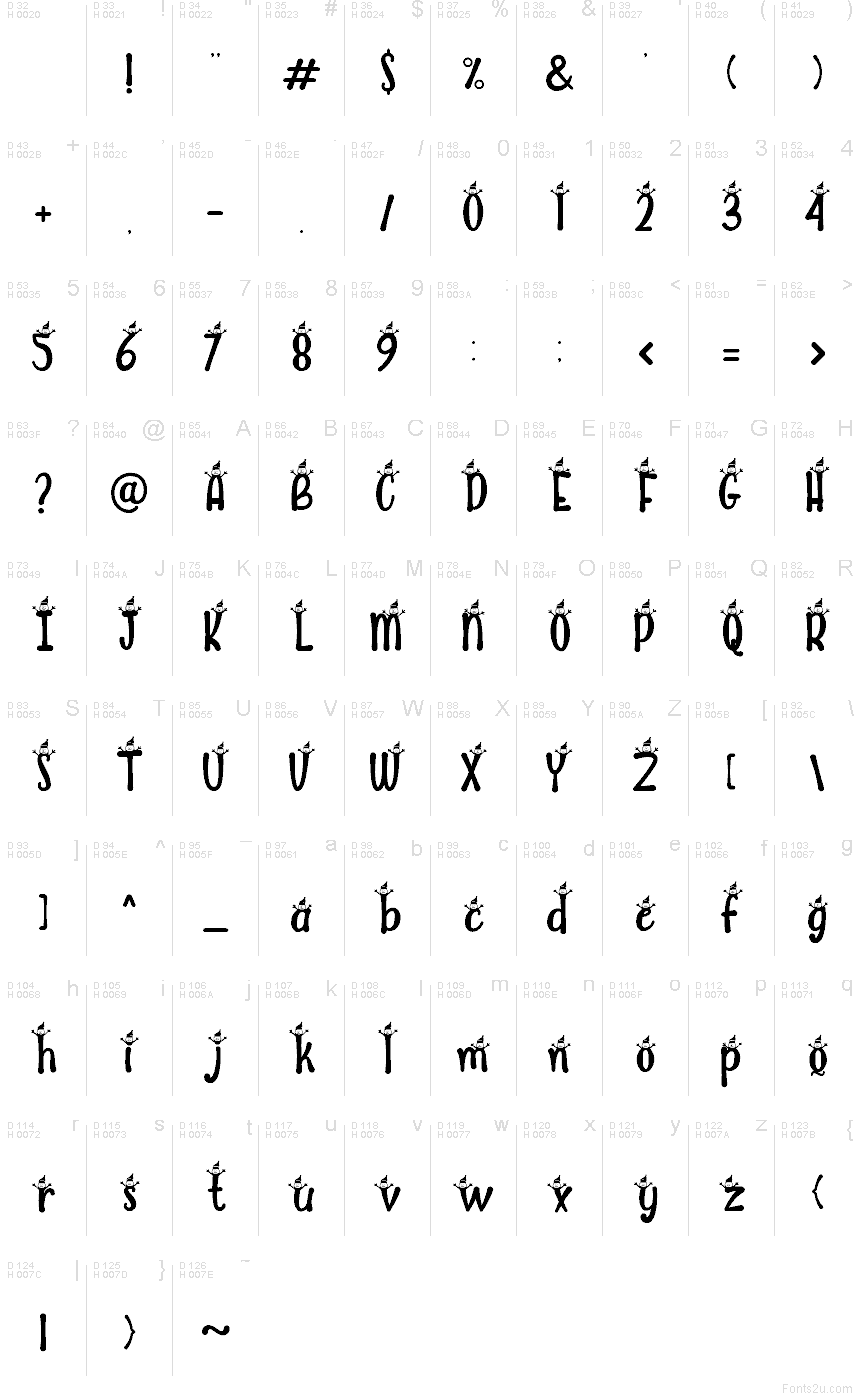
Cute Snow Snowman von Putracetol Studio ist eine kostenlose Weihnachts-Schriftart, bei der kleine Schneemänner direkt in die Buchstaben integriert sind. Das Design wirkt wie eine fröhliche Handschrift, doch jeder Buchstabe wird durch ein lächelndes Schneemann-Gesicht, eine spitze Mütze und kleine Ästchen als Arme ergänzt. So wird die Schrift nicht einfach nur zu weihnachtlichem Text, sondern zu einer verspielten Winter-Szene.
Damit eignet sie sich perfekt für Grußkarten, Geschenkanhänger, Party-Einladungen, Advents-Grafiken sowie für Verpackungen in Bäckereien oder im Bastelbedarf, wo die Schrift das Thema ganz von allein trägt. Auch für kurze Schlagzeilen, Plakat-Titel oder Social-Media-Beiträge ist sie ideal, denn die wiederkehrenden Schneemänner verleihen selbst kurzen Wörtern einen fröhlichen, lebendigen Rhythmus.